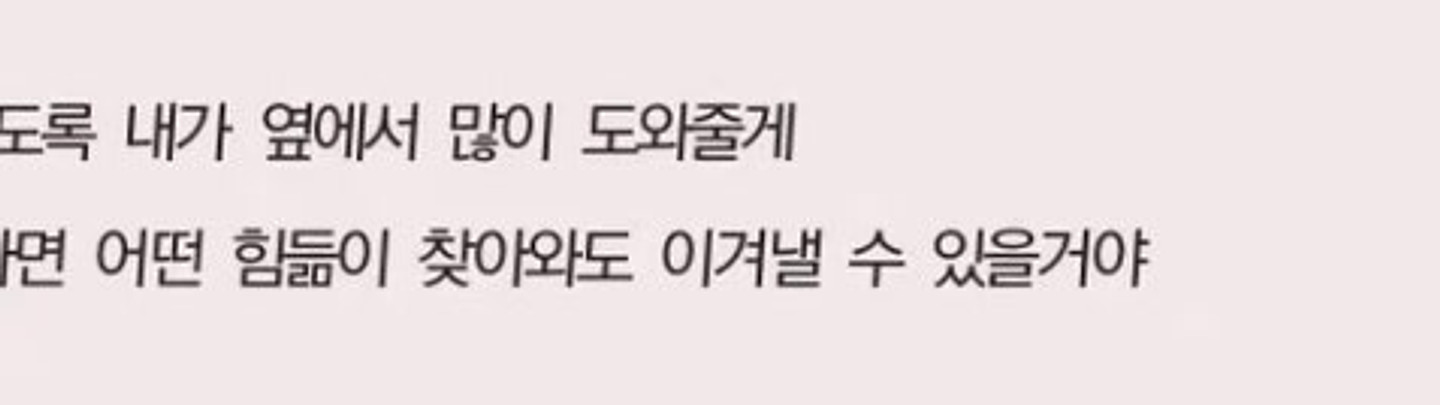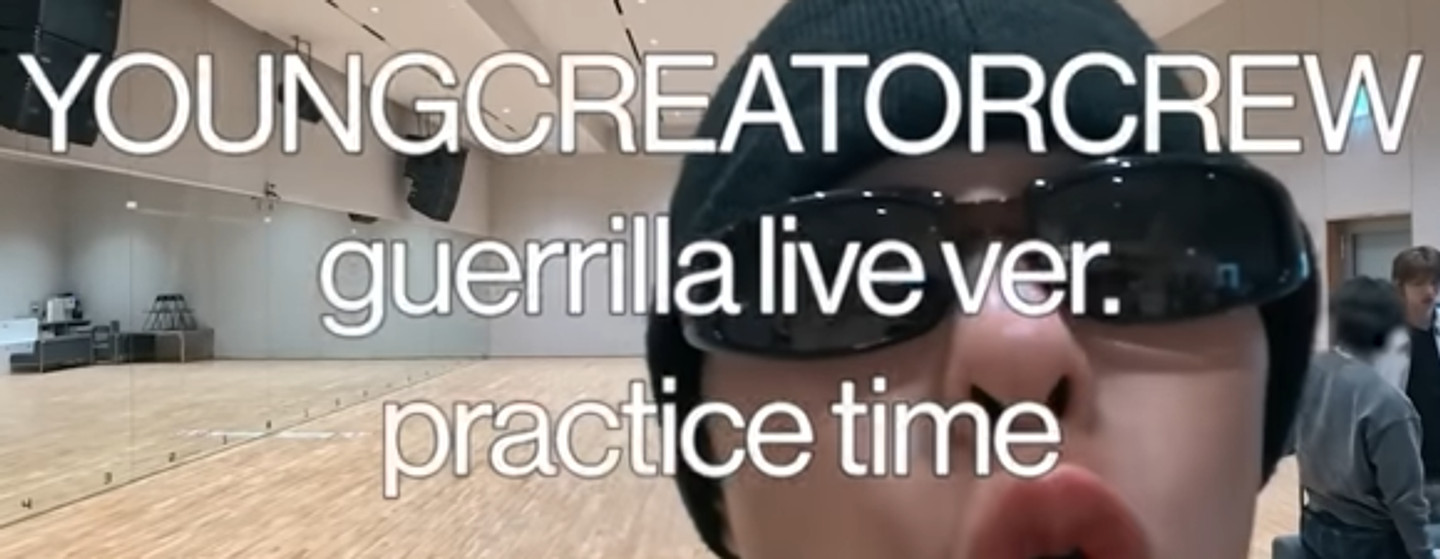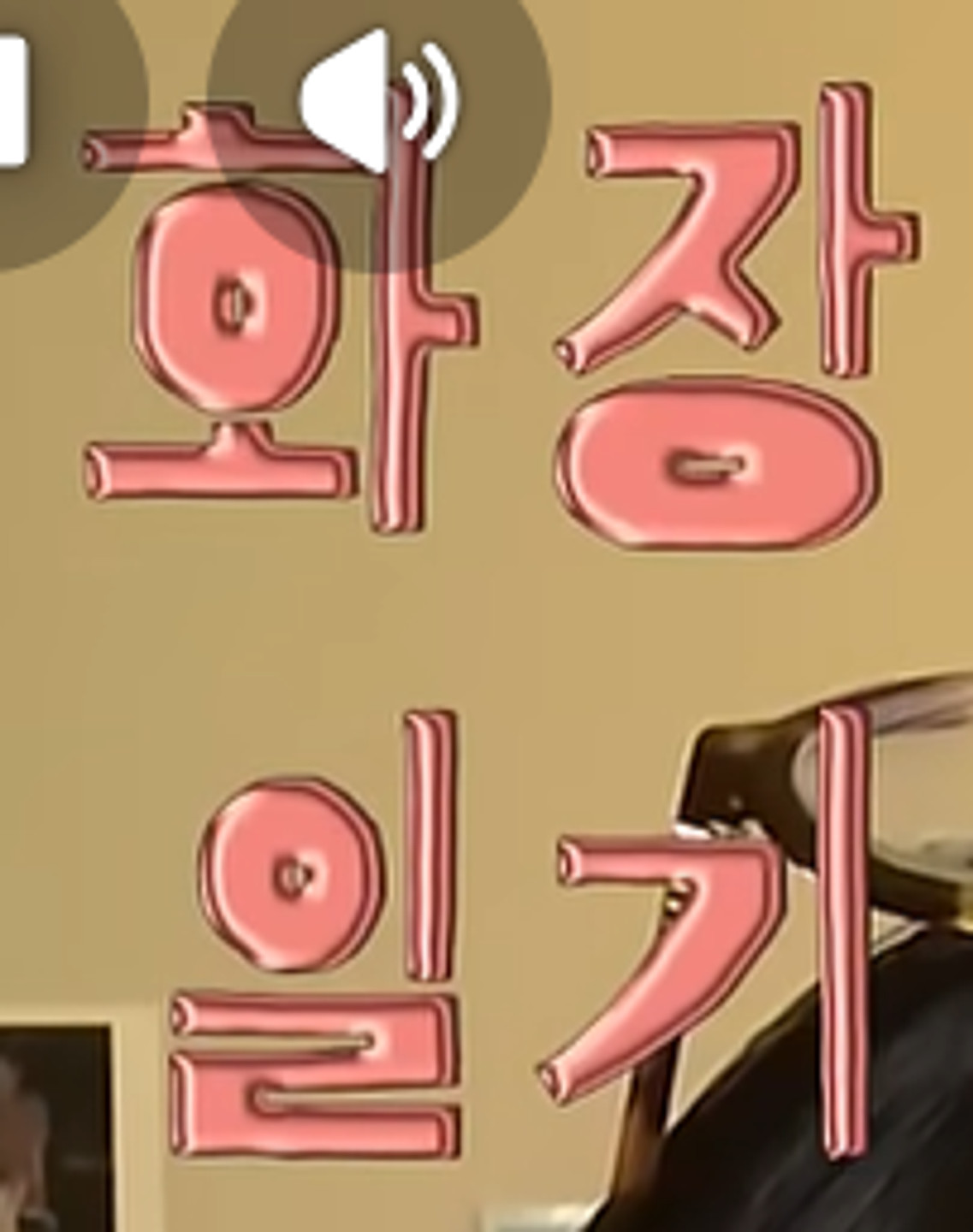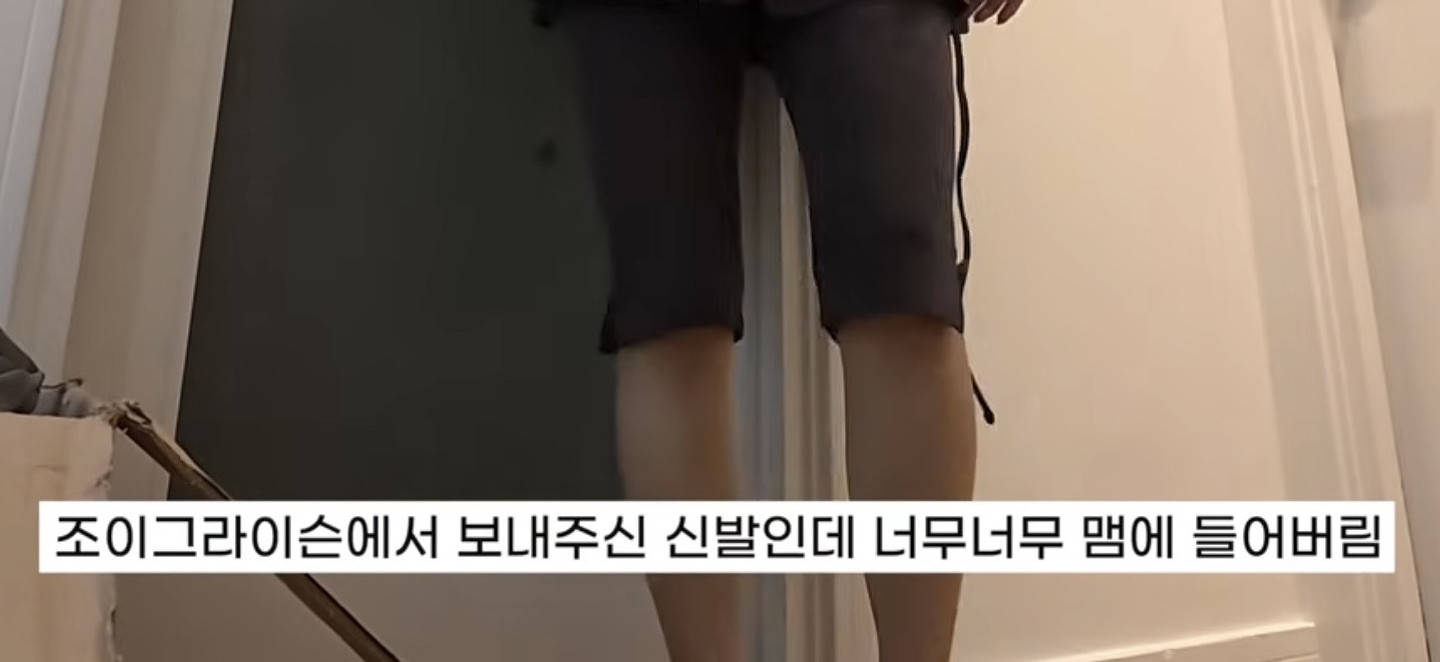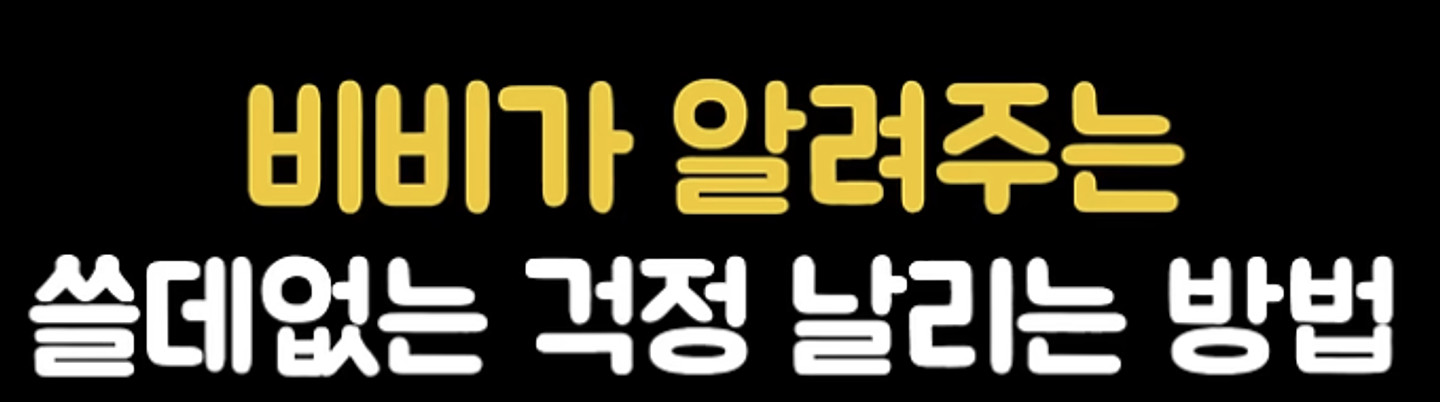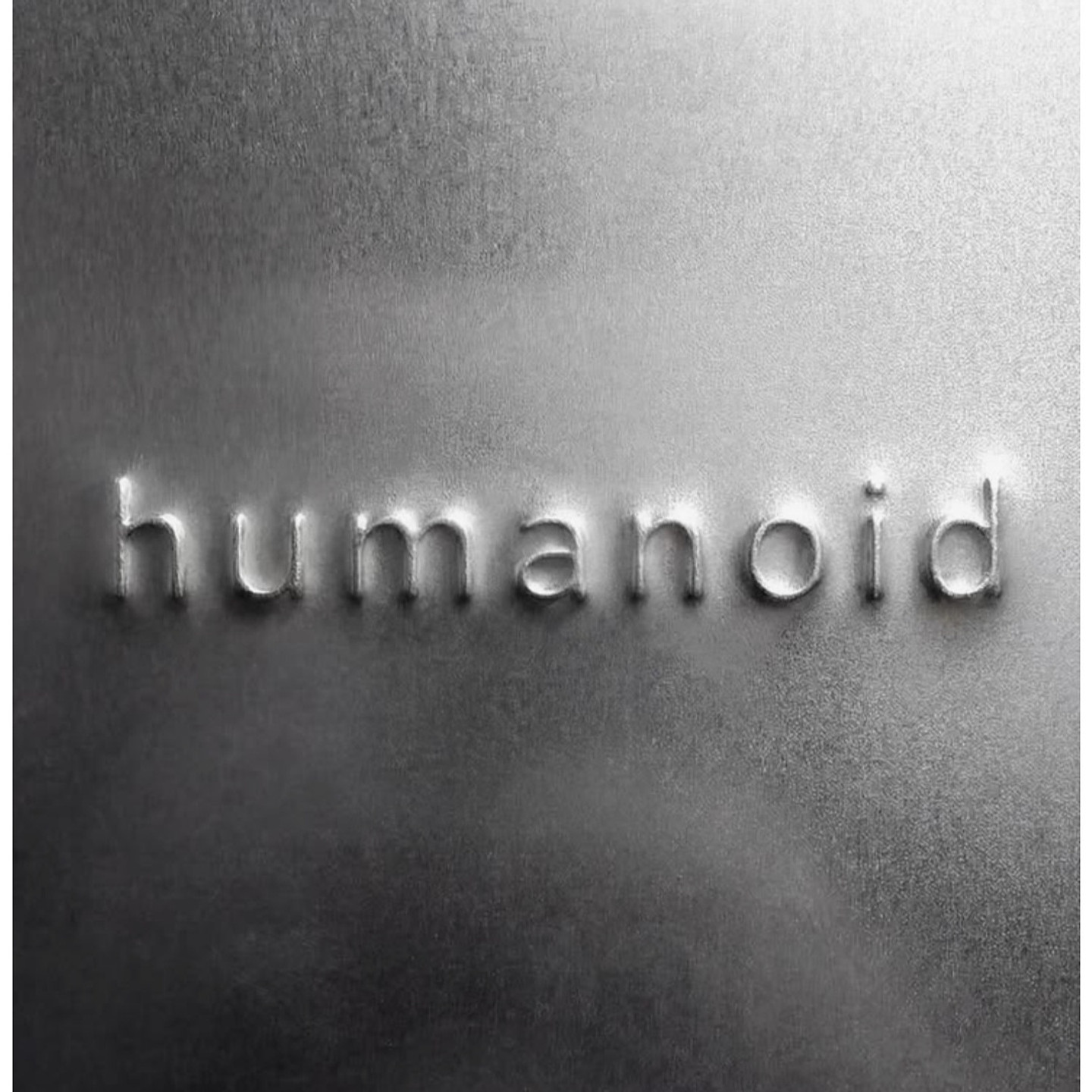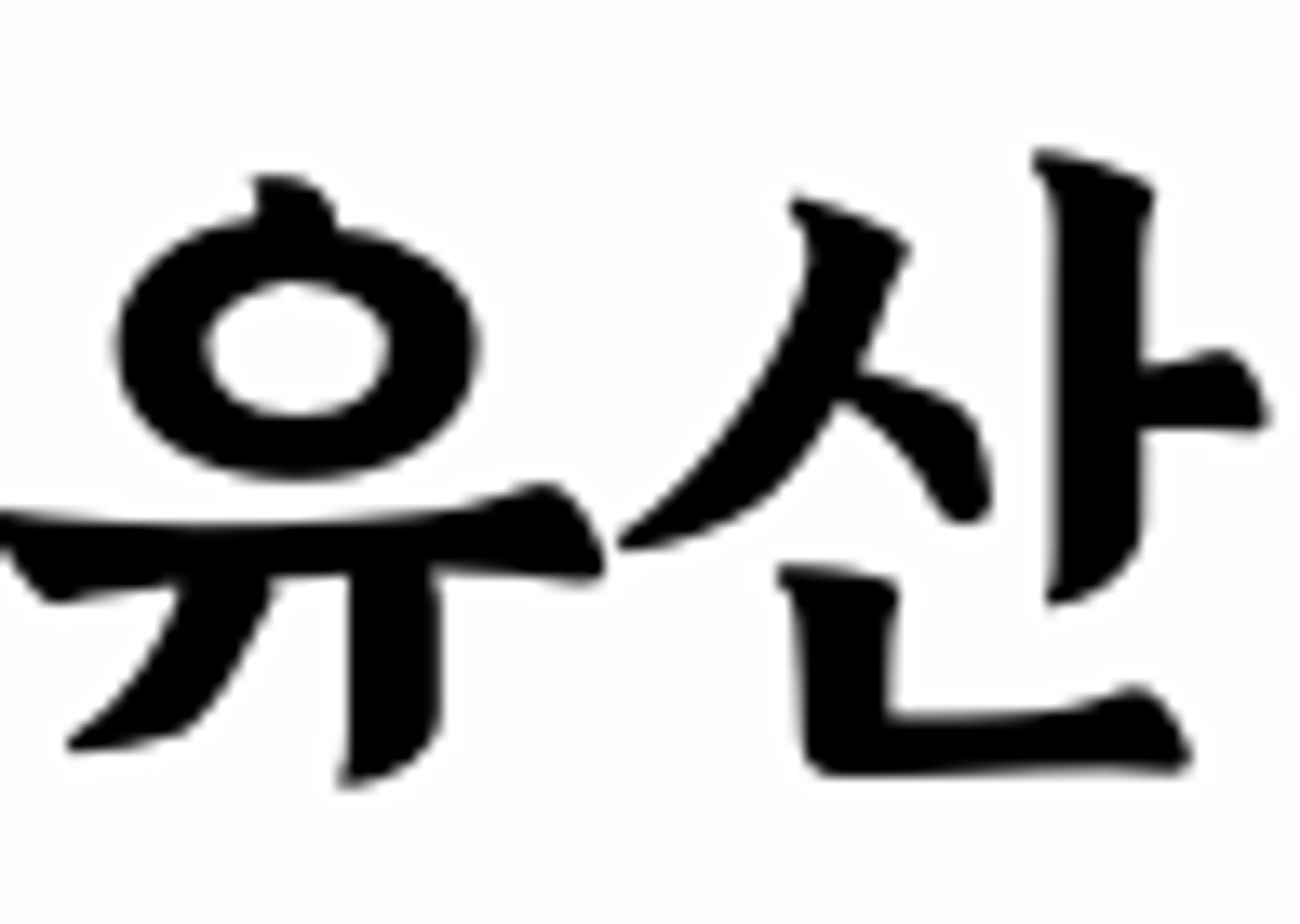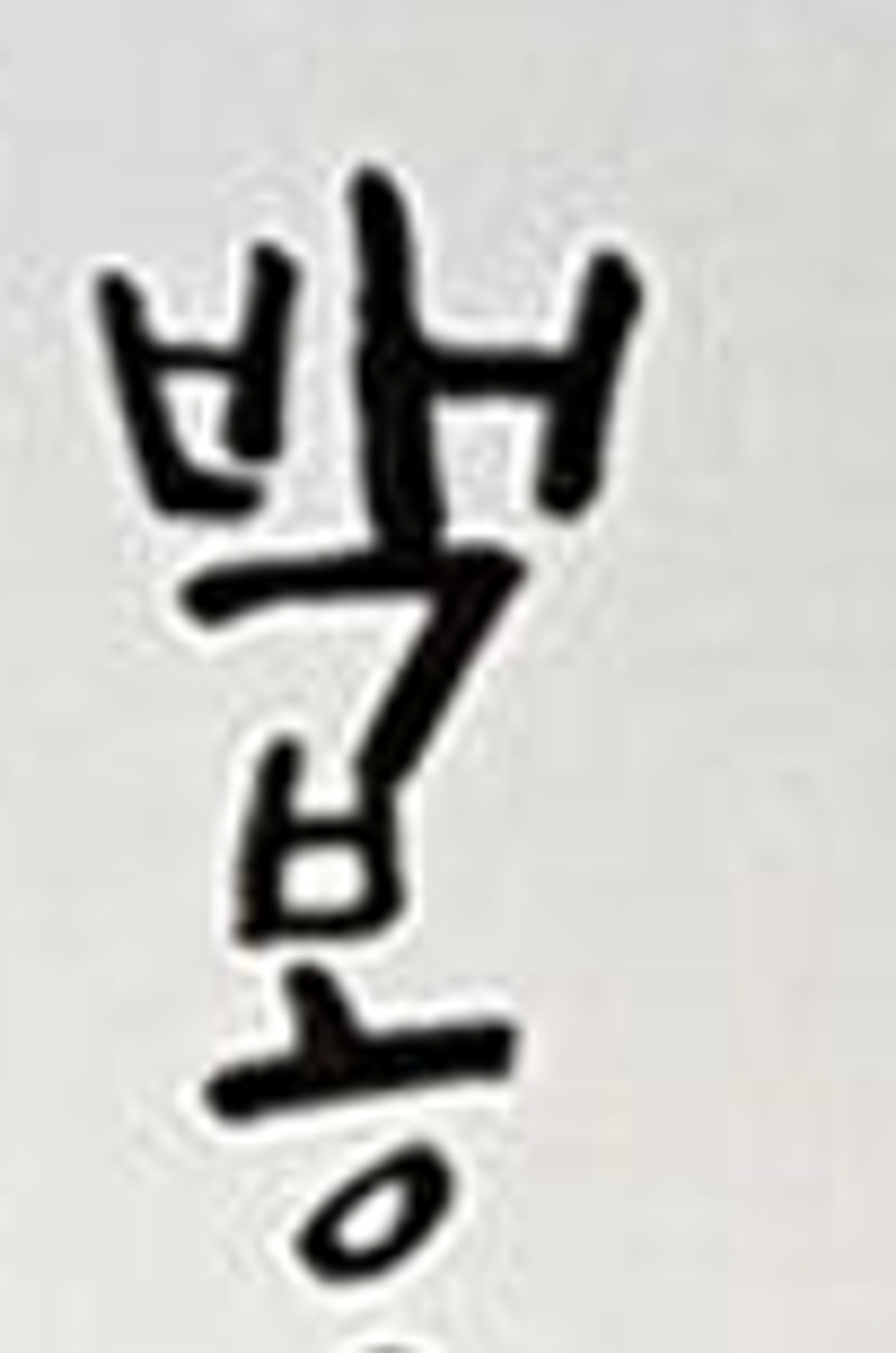
손글씨인줄 알았는데 맨 밑에 '은은한'을 보니 폰트같아서요..어떤 손글씨 폰트인가요?
이 글씨체 궁금해요..!
분홍색 박스에 들어가있는 폰트 뭔지 아시는 분 있나요? 처음에는 꼬딕씨인줄 알았는데 적어보니까 ㅍ,ㅋ,ㅅ 모양들도 다르고 영어 폰트도 다르네여 ㅠㅠ
요거 무슨 폰트 일까유??
요거 무슨 폰트 일까용???
요거 무슨 자막일까용???
메인 문구는 무슨 글씨체인지 궁금해요~
이거 폰트 아시는분 계실까요? 조선굴림체인줄 알았는데 살짝 다르네요 ㅠㅠ
뚝배기 양평해장국 에 사용된 폰트인데 폰트명 아시는분..
아래 영문폰트 이름 갈쳐주세요,^^
온글잎 같은데… 어떤 폰트일까요 ㅠㅠ
폰트 정보 궁금합니다!
교회 로고
이 글씨체 아시는 분 계실까요??
궁급해요
한자 프린트